14년 만에 바뀌는 MS의 기본 영문 폰트 파헤치기
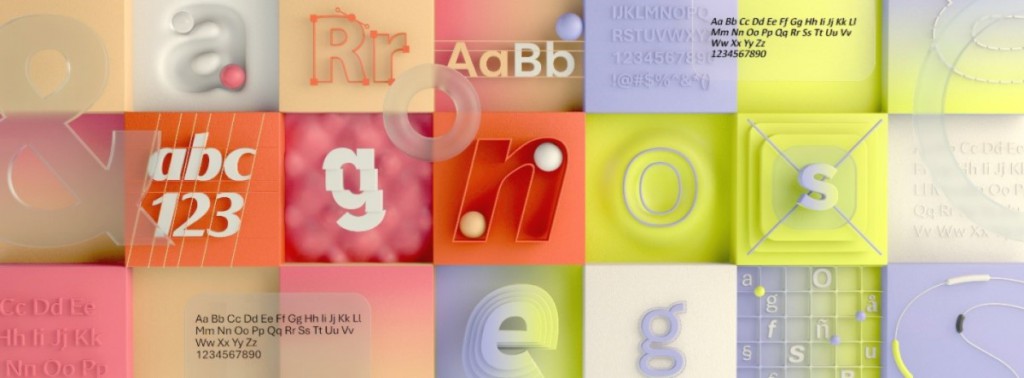
14년만의 폰트 교체?!
지난 4월, 마이크로소프트가 SNS를 통해 중대한 소식(?) 하나를 발표했습니다. 바로 2007년부터 MS Office의 기본 영문 폰트였던 ‘Calibri’를 대체할 새로운 폰트를 찾는다는 것이었죠. 후보는 총 5개. 모두 Office365 이상을 쓴다면 누구나 사용해 볼 수 있는 폰트예요. MS의 디자인팀은 트위터를 통해 많은 사람들의 의견을 듣겠다고 했어요. 그렇다면 MS의 한글 기본 폰트인 ‘맑은고딕’을 제작한 산돌구름도 가만히 있을 수 없겠죠? 산돌의 ‘라틴 폰트 전문가’ 김초롱 PD가 다섯 가지 폰트를 모두 사용해보고 각 폰트에 대한 느낌을 정리해봤어요.
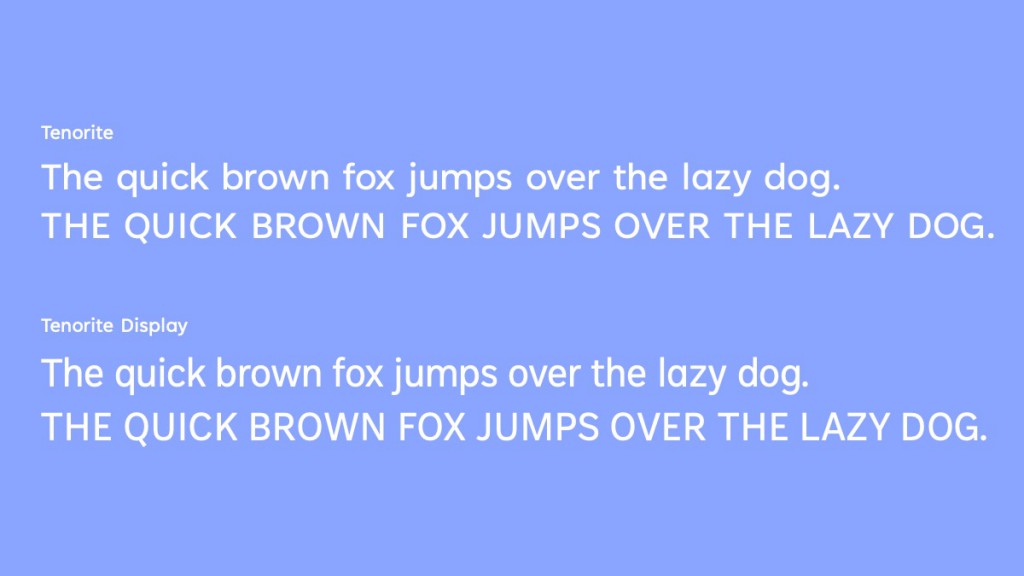
두 얼굴의 그로테스크 산스
Tenorite의 가장 큰 특징은 본문용의 Tenorite와 제목용의 Tenorite Display가 같은 패밀리로 보이지 않을 만큼 다른 인상을 지녔다는 것입니다. Tenorite는 Avenir의 영향을 받아 넉넉한 속공간과 사잇공간을 지닌 덕에 깨끗하고 밝은 인상을 주고 있어요. 특히 대소문자 ‘o’의 비율이 정원에 가까워서 이와 연계된 다른 둥근 형태의 글자들(C, G, Q, b, d, p, q, c, e)들로 인해 편안하고 따뜻하게 느껴지기도 합니다. 반대로 Tenorite Display의 ‘o’를 보면 세로가 약간 더 긴 비율로 타원에 가깝고, 이와 연계된 글자들 또한 세로비율이 약간 길고 폭이 좁습니다. 그래서 같은 글을 조판했을 때 글줄이 짧아지고, 보다 촘촘하고 단단한 인상을 주지요. 후보군의 다른 폰트들과 달리 1층 구조의 소문자 a를 적용해 단순하고 정돈된 인상을 배가시킨 느낌이에요.
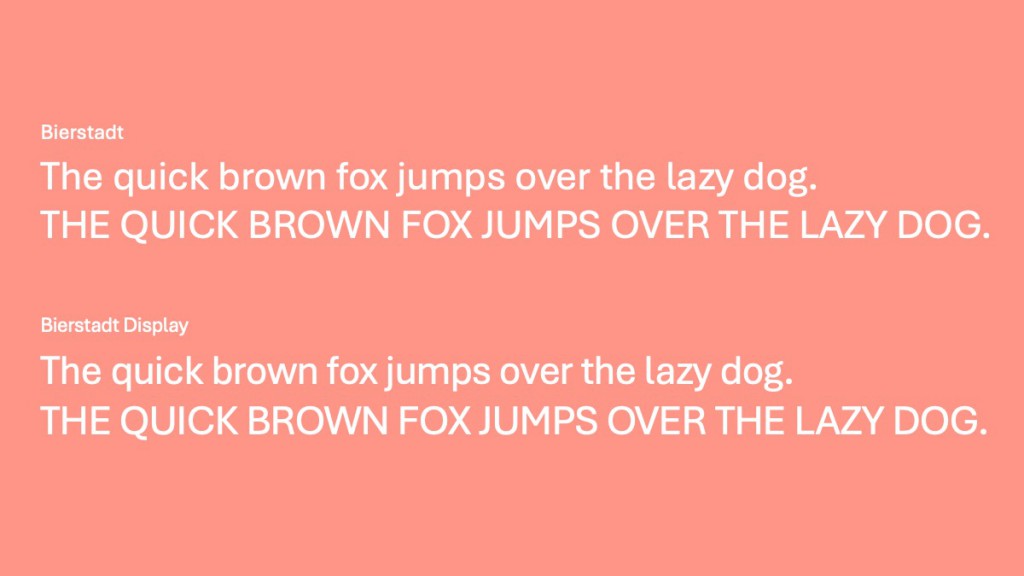
스위스 타이포그래피에 약간의 온기를 더하다
이름이 어렵죠? 우리말로는 ‘비어슈타트’라고 부르면 되는데요. Bierstadt는 언뜻 보면 네오 그로테스크 산세리프 계열처럼 보이지만, 조금 더 살펴보면 일반적인 네오 그레테스크와는 조금 달라요. 소문자 f, t의 획맺음은 세로직각 잘림으로 Helvetica를 따라갔으나, b나 n 등에서 세로획과 곡선이 만나는 곳의 구조는 매끈하게 연결되는 일반적인 네오 그로테스크의 구조가 아닌 획의 쓰기 순서를 엿볼 수 있는 구조를 따랐지요. 이외에도 2층 구조의 소문자 g, 둥근 형태를 강조한 대문자 G, 중간 아랫부분에 공간을 만들어준 대문자 M, 곡선을 적용한 대문자 Q의 꼬리와 소문자 l의 아래쪽 획을 보면, Helvetica나 다른 스위스 타이포그래피의 영향을 받은 포트들과는 다른 특징을 가졌다고 할 수 있어요. 이러한 특징들때문에 기존의 네오 그로테스크 계열의 폰트들보다는 약간 부드러운 인상을 전달하죠.
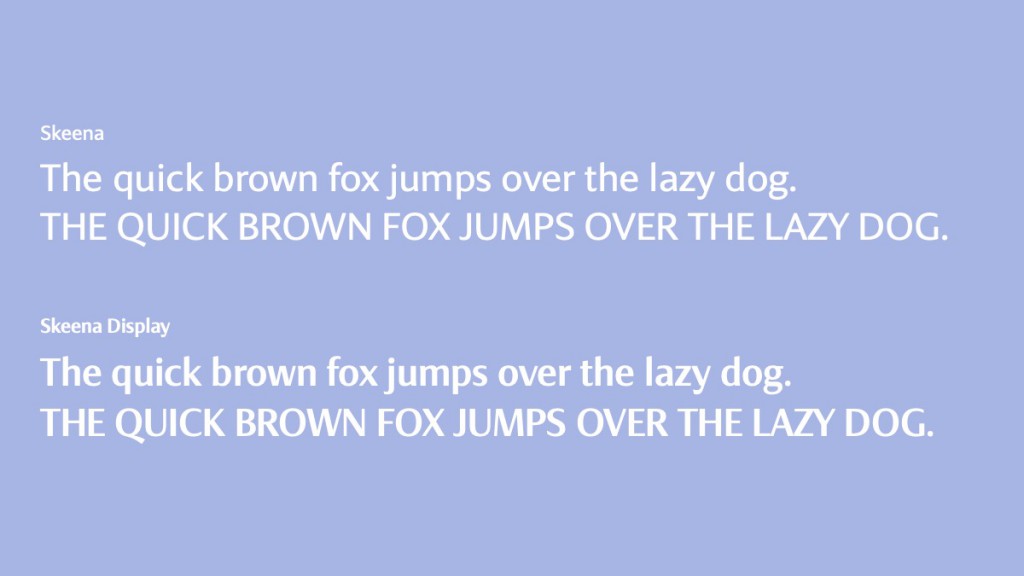
획의 대비가 특징인 휴머니스트 산스
Skeena는 다섯 개의 후보군 중 획의 대비가 가장 잘 보이는 폰트예요. 특히 Skeena Display는 거의 휴머니스트 세리프 계열의 폰트가 연상될 정도의 획대비를 갖고 있어요. 뿐만 아니라 어센더가 시작하는 부분의 획이 사선으로 그려졌고요. 소문자 c, e, s, t, j, y의 아래쪽 둥근 획의 맺음은 예각으로 처리되어 있어요. 이것을 보면 좀 더 날렵하게 보일 수 있도록 납작펜으로 썼을 때 나타나는 형태를 특징적으로 반영한 것처럼 보입니다. 대문자 C나 S를 보면 전반적으로 열린 구조를 차용하고 있다는 점도 Skeena가 휴머니스트 산스의 특징을 잘 살린 폰트라는 것을 말해주고 있어요.
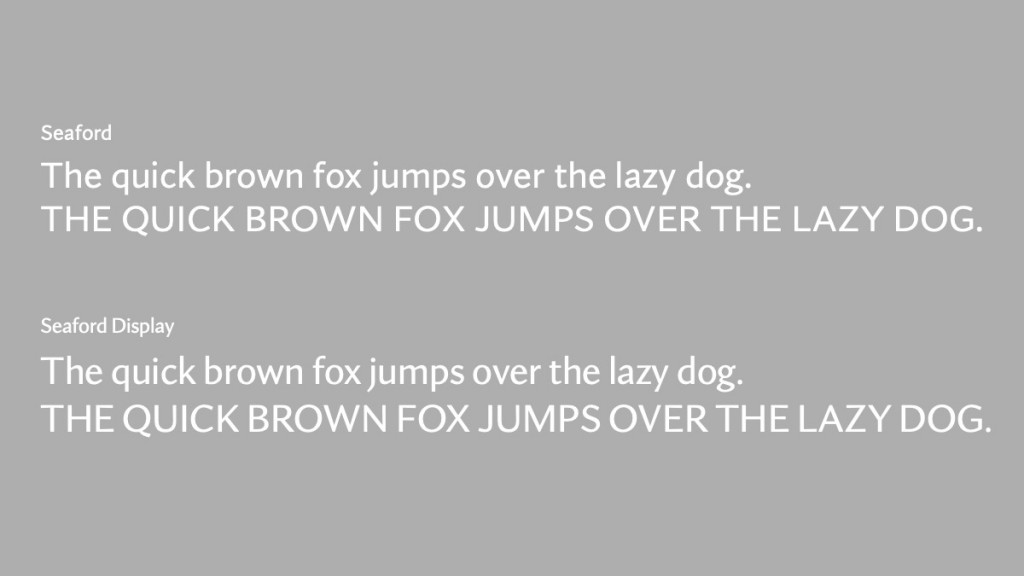
휴머니스트 세리프의 뼈대를 지닌 휴머니스트 산스
왜인지는 모르겠지만 처음 Seaford를 봤을 때, Hans Eduard Meier의 Syntax라는 폰트가 생각이 났어요. 아마도 Syntax와 Seaford 모두 ‘휴머니스트 세리프의 뼈대와 비율을 가진 산세리프’라는 컨셉에서 시작했기 때문이겠죠? 크고 넉넉한 대문자와 오밀조밀한 소문자의 크기 차이와 비율의 관계 또한 휴머니스트 세리프가 가진 특징을 잘 반영한 것 같아요. 특히 소문자 a의 윗쪽 곡선이나 c의 아랫쪽 곡선이 급격하게 꺾이는 것을 볼 수 있는데요. 큰 크기에서는 조금 과하지 않나 싶은 생각이 들 수 있는데, 작은 크기에서 보면 이 부분이 휴머니스트 골격의 인상을 강화하는데 상당한 역할을 하고 있다는 것을 깨닫게 됩니다.
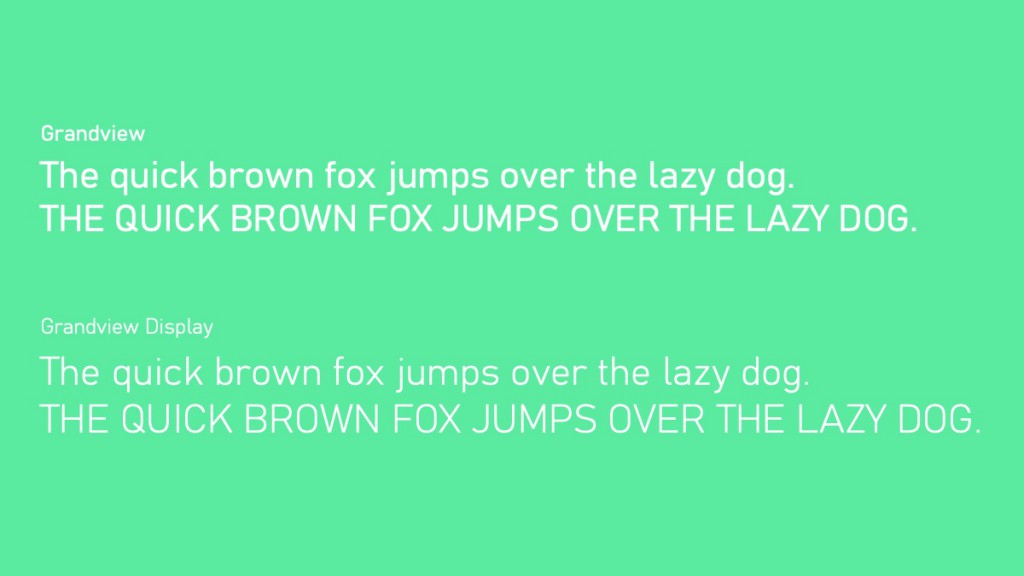
Din의 DNA에 가독성을 입힌 지오메트릭 산스
Grandview는 한국에서도 많이 사랑받는 Din의 뼈대 및 특징을 그대로 살리되 소문자는 약 4~5%, 대문자는 약 2% 정도 너비를 넓힌 폰트입니다. 덕분에 장문의 텍스트도 소화 가능하죠. Din과 구별되는 뚜렷한 특징이 없는 것은 다소 아쉽지만, 날씬한 너비때문에 가독성이 떨어질까 우려되어 본문용으로는 사용을 꺼렸던 Din 사용자들에게는 좋은 소식이지 않을까 싶어요. 여담이지만 Grandview를 제작한 Aaron Bell은 산돌구름과도 친한 사이에요. 한글에도 관심이 많아 직접 한글 폰트도 제작하고 있고요. 혹시 모르죠? Grandview가 MS의 차기 영문 기본 폰트로 선정된다면 맑은고딕 이후의 한글폰트에 대한 일종의 힌트를 얻을수도요..?!
What’s next?
MS는 위 다섯가지 후보들을 놓고 수개월 동안 테스트와 의견 수렴을 진행할 거라고 합니다. 개인적으로는 후보 중에 세리프 폰트가 없는 부분이 조금 아쉽더라고요. 트위터 반응들을 살펴보면 Calibri 이전의 기본 영문 폰트였던 ‘Times New Roman’을 돌려내라는 과격한 표현부터, Calibri를 제발 건들지 말아달라는 애원, 차라리 ‘Comic Sans’는 어떠냐는 놀림 등 다양한 의견들이 쏟아져나오고 있어요.
아무쪼록 폰트를 사랑하는 여러분도 관심갖고 지켜봐주시면 좋을 것 같아요. MS Office가 비즈니스 생태계에 막강한 영향력을 갖고 있는만큼, 어떤 폰트가 선정되느냐에 따라 우리의 타이포그래피 문화에도 분명 영향이 있지 않을까요?